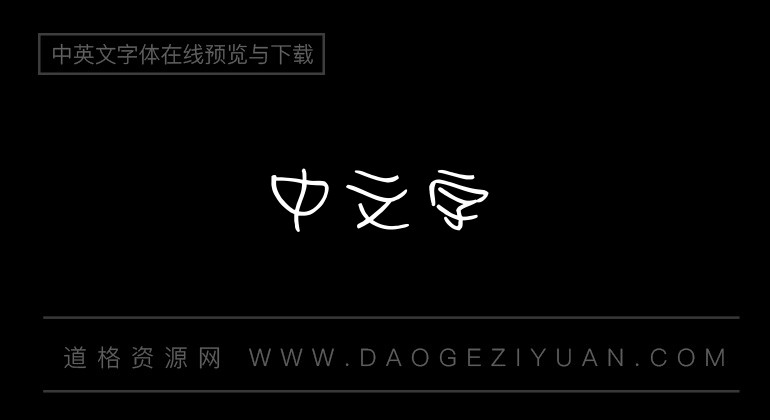
金梅美工新创字体
金梅美工新创字体是一款品牌新创的字体,它以极具设计感的折线字体作为基础,又加入了更多的细节和调整,使字体具有更多的设计感和灵动感。金梅美工新创字体有着流畅的线条,它拥有独特的细节,比如细长的笔画,折线,曲线等,使字体具有时尚感和现代感。它也具有良好的可读性,可以更好地传达信息。
金梅美工新创字体是一款非常不错的手写艺术字体,具有很好的视觉感,适合于文化类的宣传设计、商业类品牌的广告和产品包装设计以及个性化文字排版等较多场景。